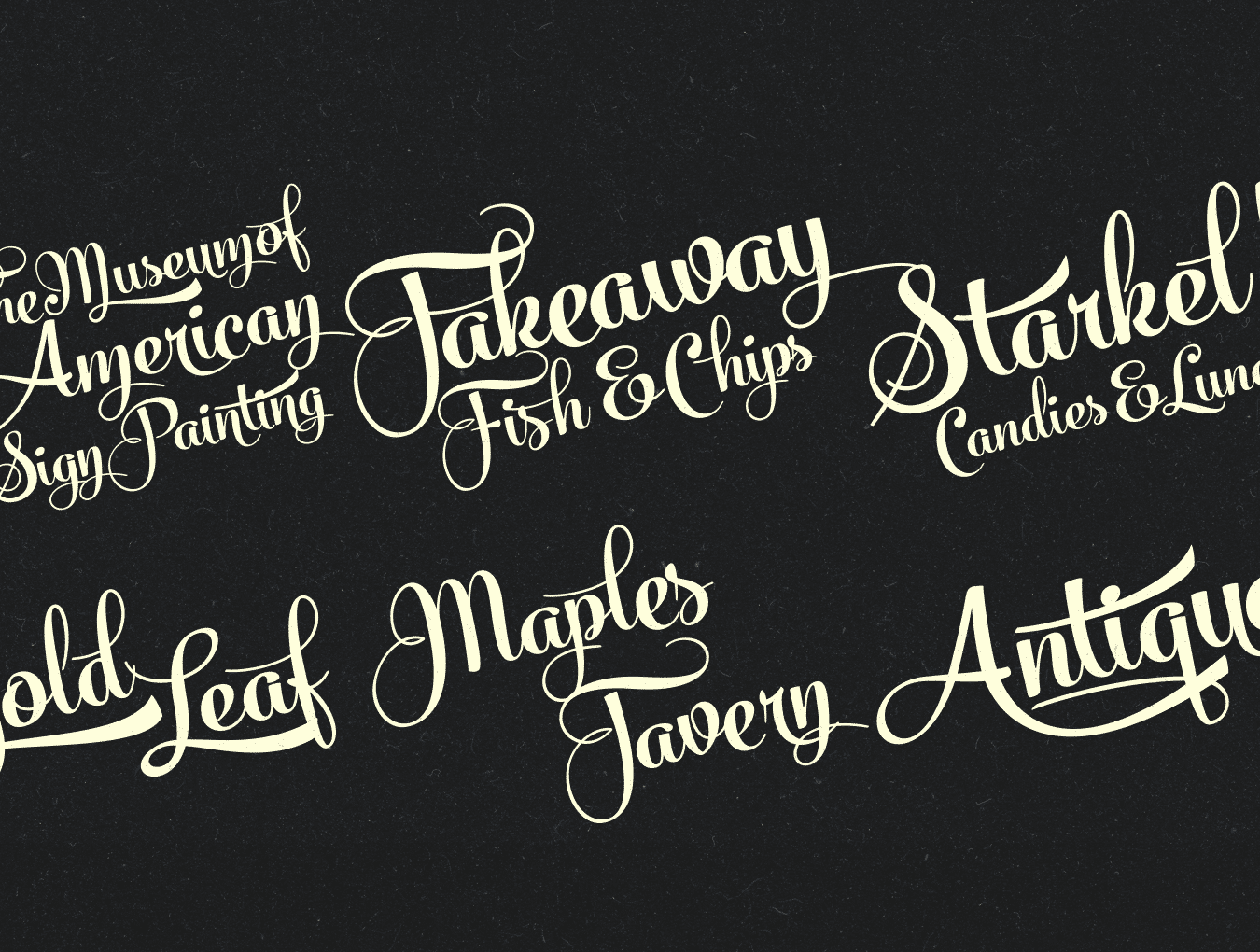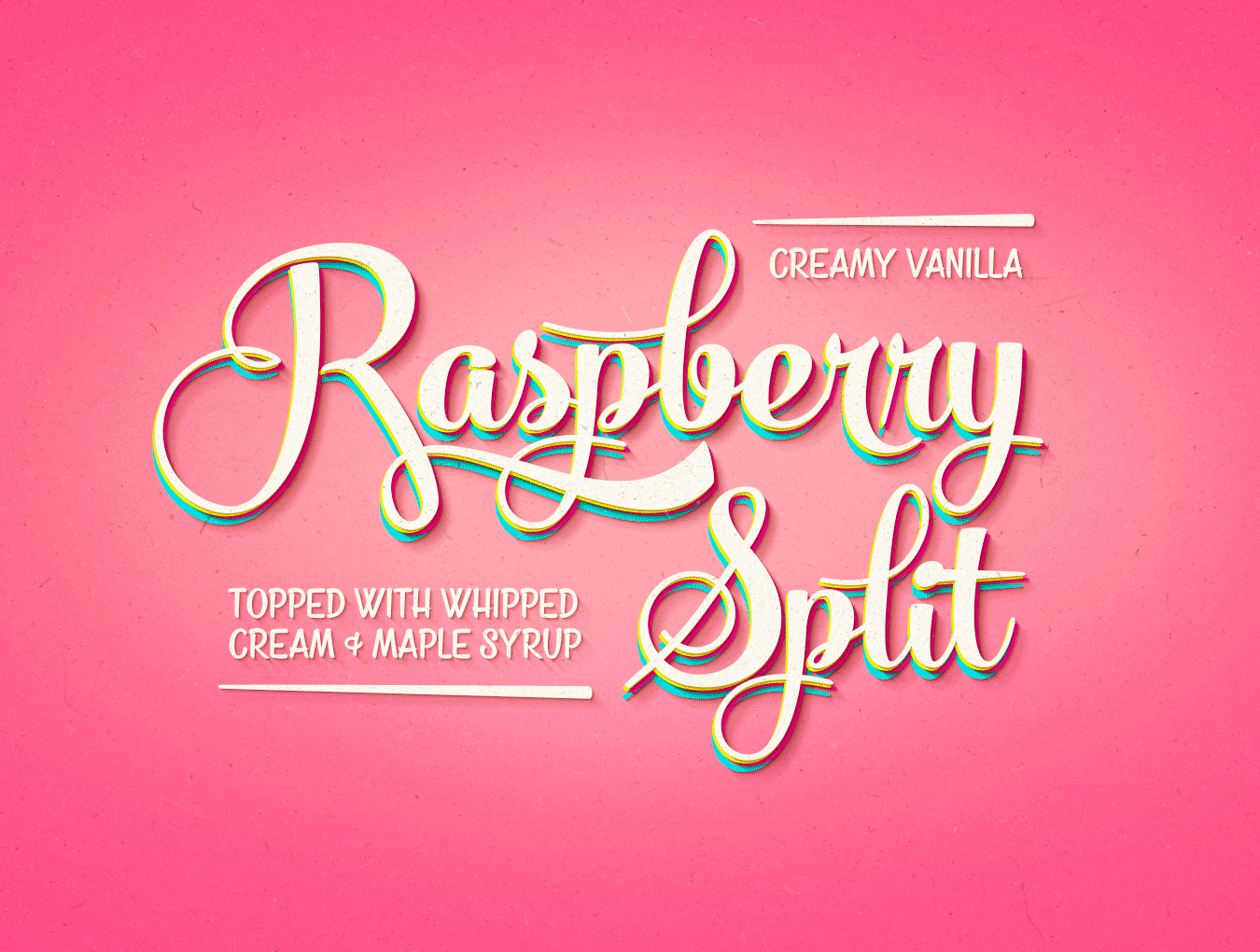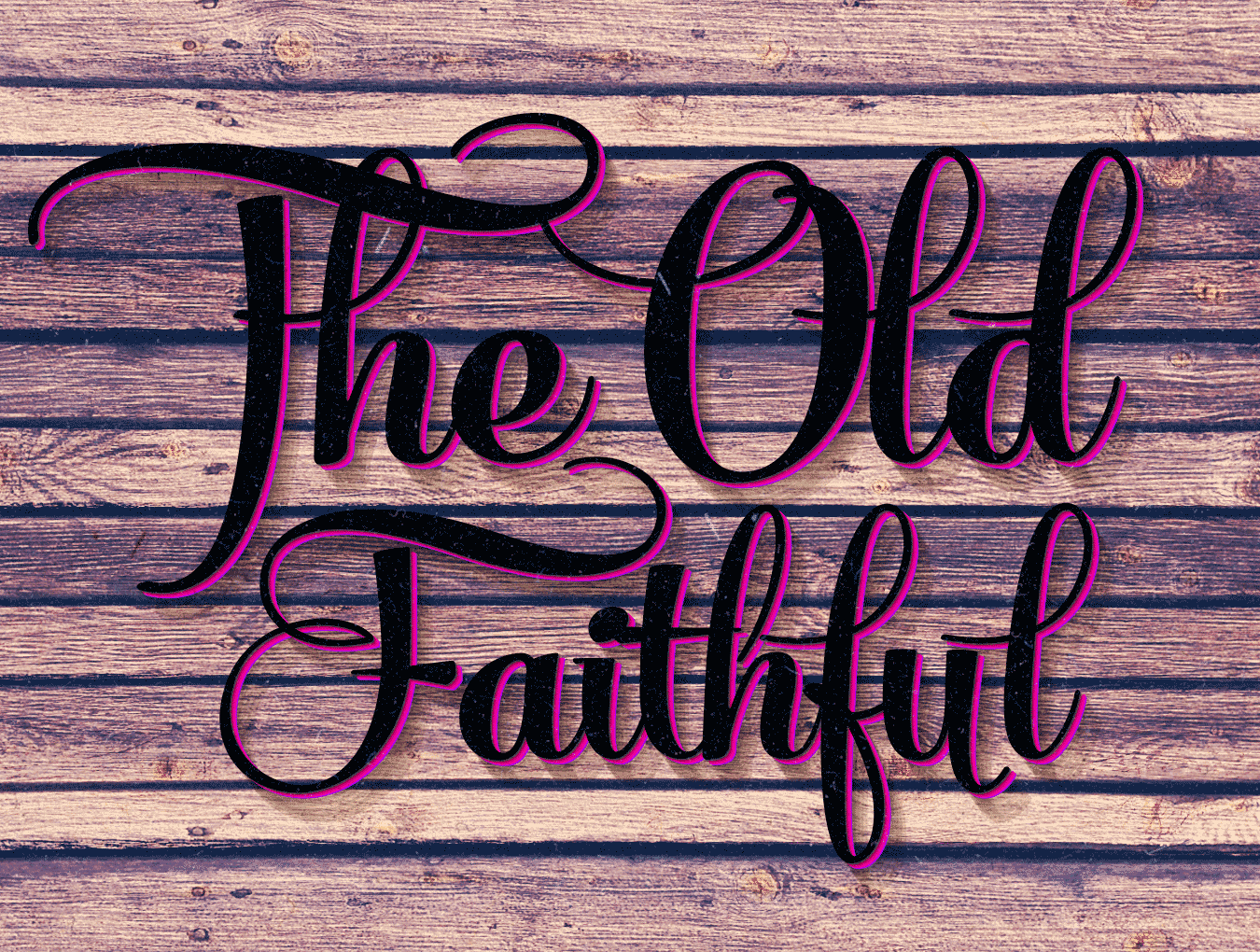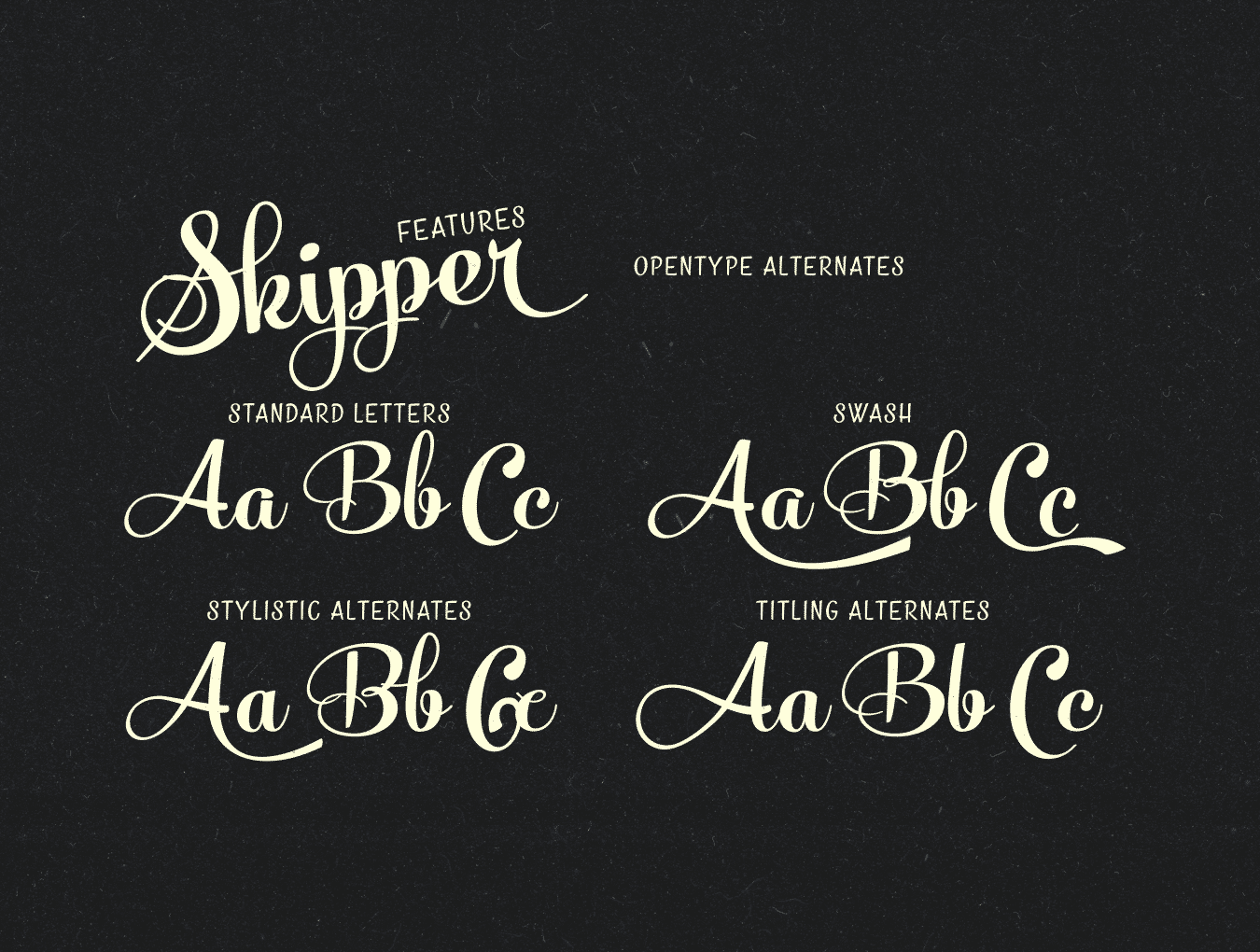
大胆流畅的连接脚本,船长
Bold & flowing connect script, Skipper
船长是一个大胆而流畅的连接脚本。 船长为每个基本字母配备三个备用字符:点击任何OpenType精明程序上的Swash,Stylistic或Titling Alternates来创建自定义外观设计。 在船长里面有一套35个用于支撑字体的装饰品。从Glyph Palette访问饰品。